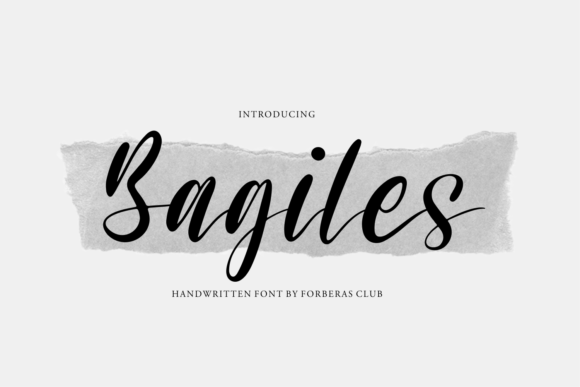
Bagiles - это волшебный шрифт, созданный с элегантностью.
Ищите ли вы шрифты для Instagram или каллиграфические шрифты для проектов DIY, этот шрифт превратит любую творческую идею в настоящее произведение искусства!